1、局部变异
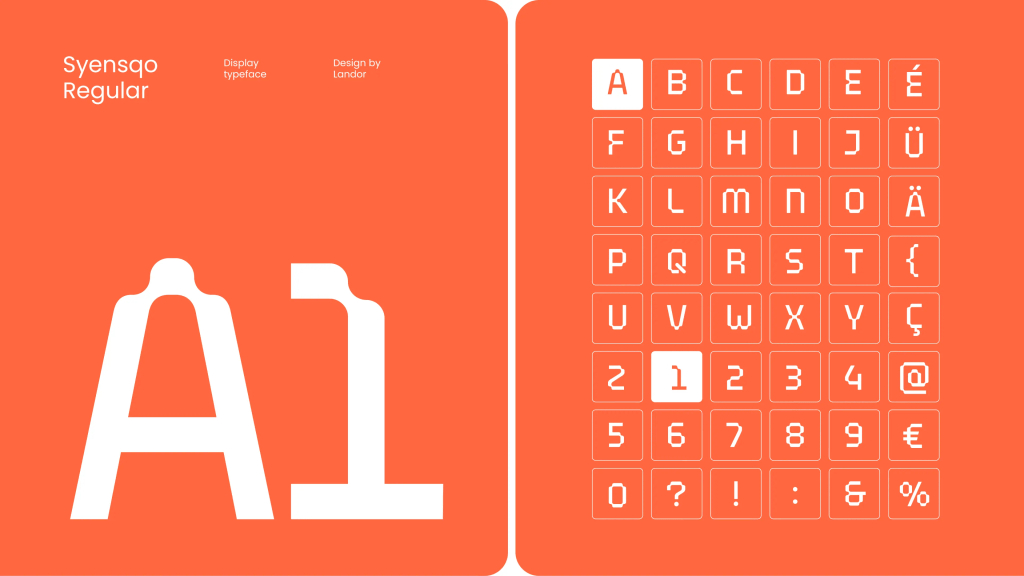
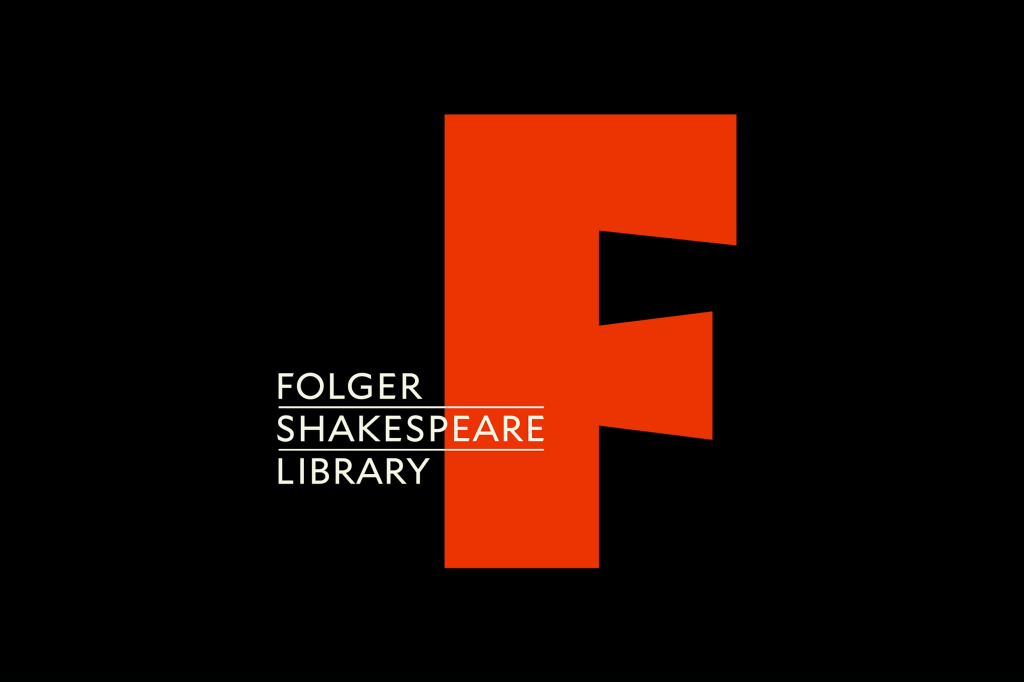
负形
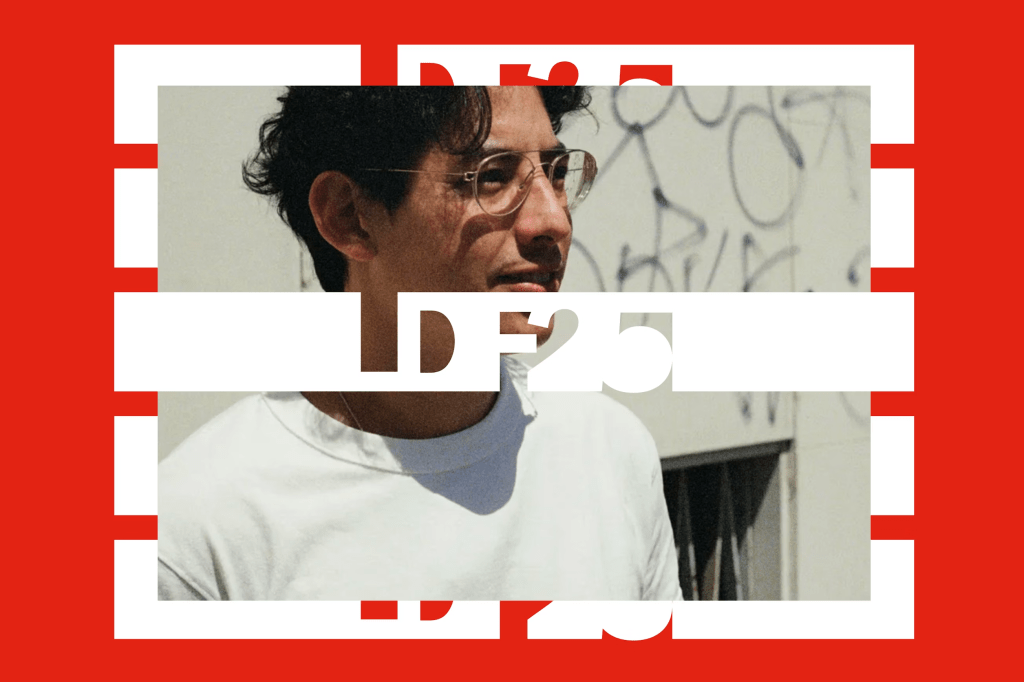
线条化笔画
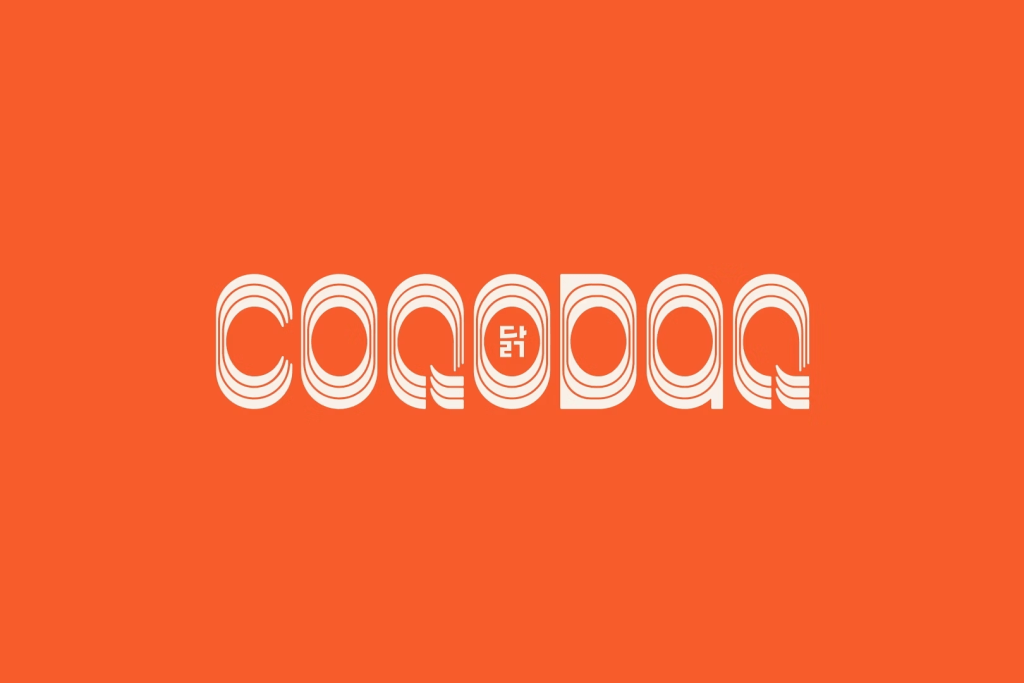
非曲线字体
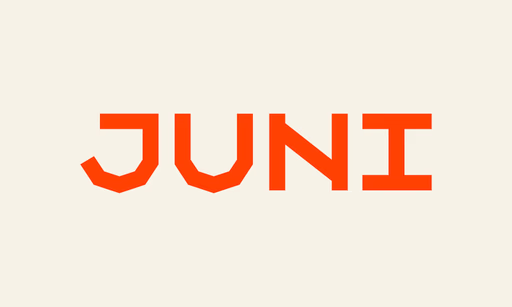
笔画上下置换
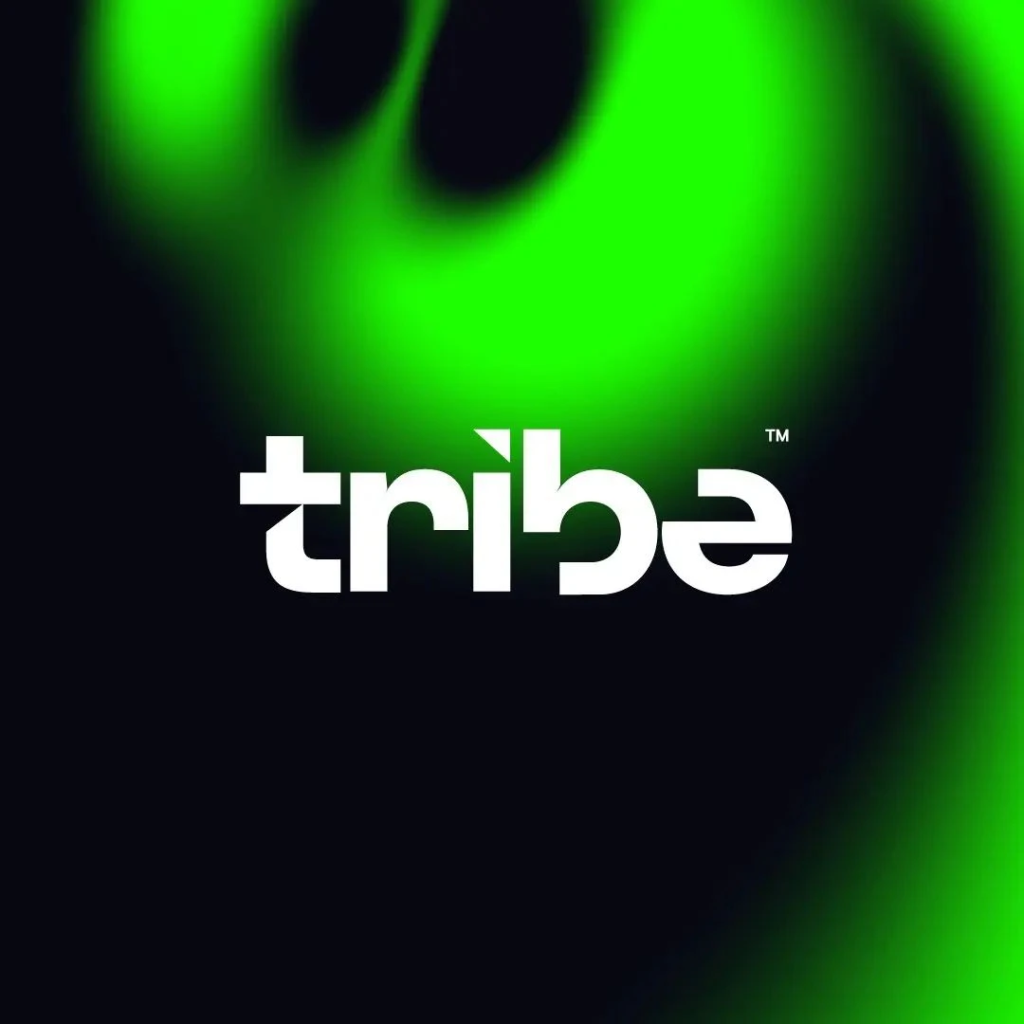
手绘线条
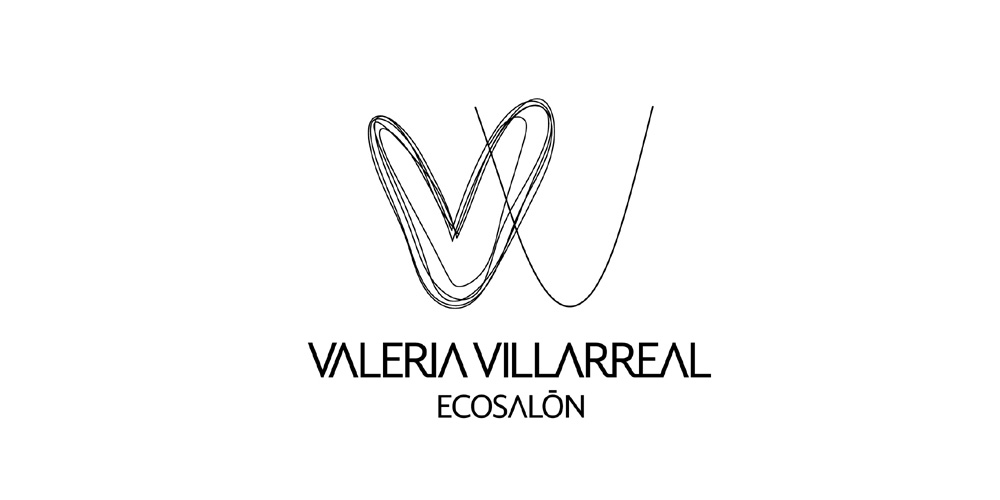
多用手绘
一、解构与重塑
这一类风格的核心是“破坏”:打破字体的传统骨架、比例和笔画规律,然后在废墟上重建新的视觉秩序。
1. 重塑结构 (De-form)
- 核心特征:设计师们正在用“重塑结构”反抗常规,与“平庸”和“干净美学”背道而驰,打破了字体的骨架,渴望占据更大的画面版块,将字体的可能性无限延展。
- 设计手法:不再严格遵循字重平衡、宽度一致、字形比例,而是享受更多实验乐趣。这种变形手法在过去几十年是不被提倡的,如今成为前卫设计的标志。
- 视觉感受:反抗、力量、不稳定、视觉冲击
2. 断裂与破碎
- 核心特征:将文字的笔画采取剪切、错移、分解、手撕或呈现缺口等方法,使其产生断裂、破碎、虫蛀、粗犷等感觉,常能激发心灵的极大震撼。
- 设计手法:通过在笔画上制造“伤口”或错位,打破文字的流畅性。
- 视觉感受:冲突、解构、工业感、不完美美学
3. 多维/伪立体
- 核心特征:通过笔画的重叠、投影、色彩分层,创造出超越平面的立体感和空间感。后面的笔画叠住前面的笔画,副笔画叠住主笔画,或者相互重叠。
- 设计手法:利用错视和阴影,破坏字体的平面属性。
- 视觉感受:科技、层次、动态、力量
4. 负空间“反”击 (Counter Attack)
- 核心特征:让负空间(笔画包围的空隙)成为主角,借用非现实元素,做视觉减法,让造型内部呈现出特殊的视觉愉悦感,也传达出一种更复杂的技术感。
- 设计手法:通过压缩、扭曲或夸大负空间,使字形变得抽象而具有双重解读性。
- 视觉感受:巧妙、现代、技术感、极简
5. 故障/像素风
- 核心特征:模拟电子设备的故障效果(拉伸、错位、色差)或低分辨率时代的像素块。
- 视觉感受:数字感、赛博朋克、复古未来、科技感
二、动态与感知
这一类风格关注字体的“运动感”和“感官体验”,它们不再是静止的图形,而是流动的能量。
1. 流动 (Flux)
- 核心特征:元素们能够运动、生长、扩展和变形,以动态的方式进行交流,为品牌注入活力。这是过去几年逐渐流行且愈发成熟的趋势。
- 设计手法:笔画模仿液体、烟雾、织物的形态,充满有机感和不确定性。
- 视觉感受:灵动、未来感、能量、不可预测
2. 光感/渐变 & 3D渲染
3. 混沌手写 (Chaotic Scripts)
三、复古与未来
这一类风格在时间轴上做文章,将过去的风格元素进行重组、扭曲或夸张,制造出一种“熟悉又陌生”的超现实主义体验。
1. 随心所欲 (Whatever)
- 核心特征:怀旧风潮的极端化,受Z世代影响,融合虚无主义的油渍摇滚、像素游戏、90年代锐舞传单等元素。
- 设计手法:粗体大字、渐变色彩、立体阴影的复古字体再次流行,且风格更杂糅。
- 视觉感受:反叛、复古未来、亚文化、高能量
2. 怪诞 (Quirk)
- 核心特征:根植于稳固的无衬线字体基因,又通过大胆、意外的细节(如不协调的笔画弧度、独特的衬线处理)带来惊喜。
- 设计手法:在符合整体视觉规范的前提下,注入一种“松弛感”或“随机感”。
- 视觉感受:幽默、独特、松弛、眼前一亮
3. 包罗万象 / 极繁主义 (Everything All of the Time)
四、造字方法论(非风格,是手段)
除了上述风格趋势,从技术实现手段上看,变异字体还可以通过这些具体的“动作”来创造,这些是设计师手中的工具箱: